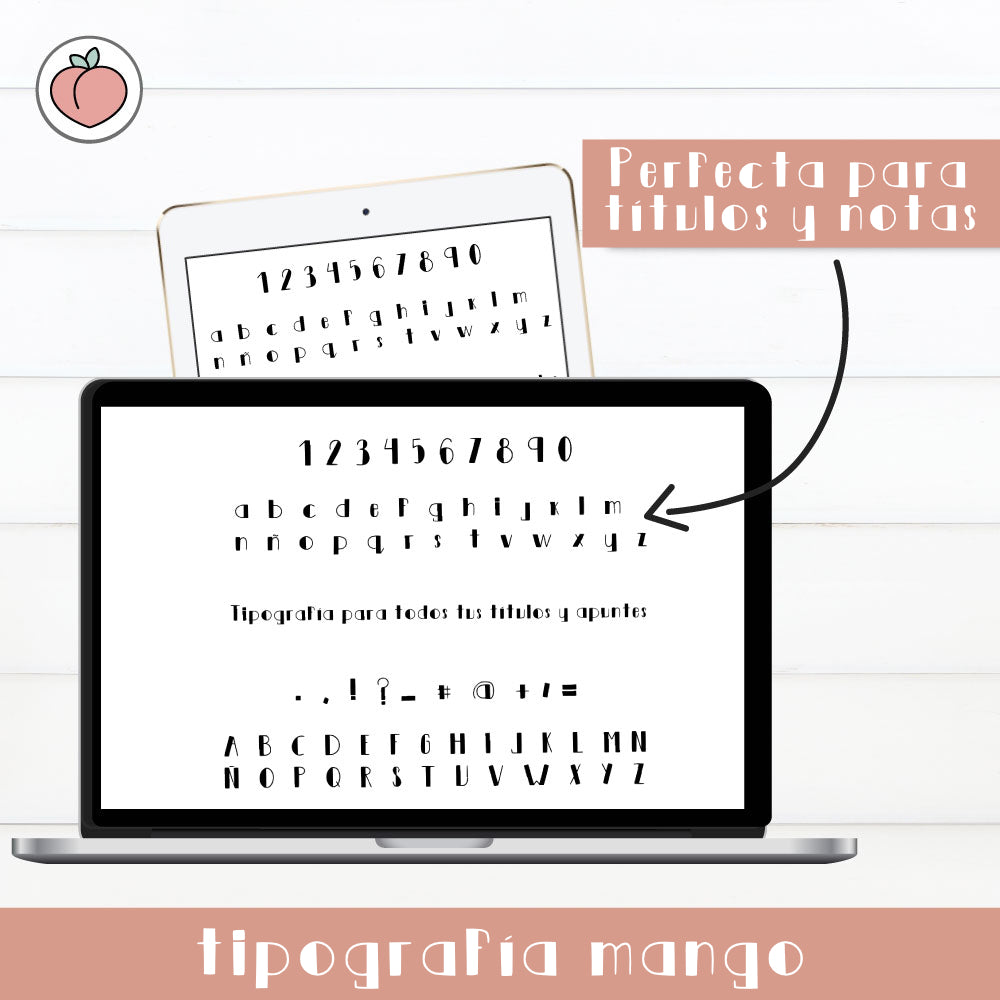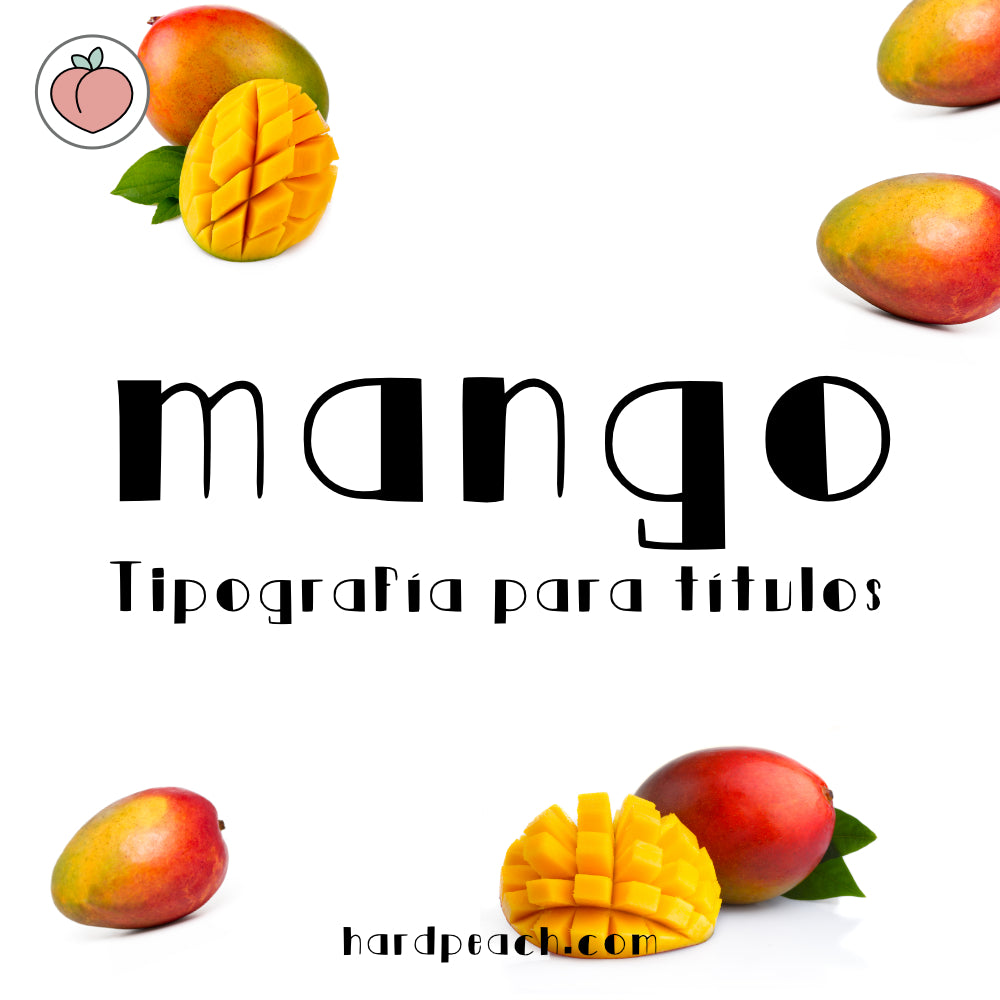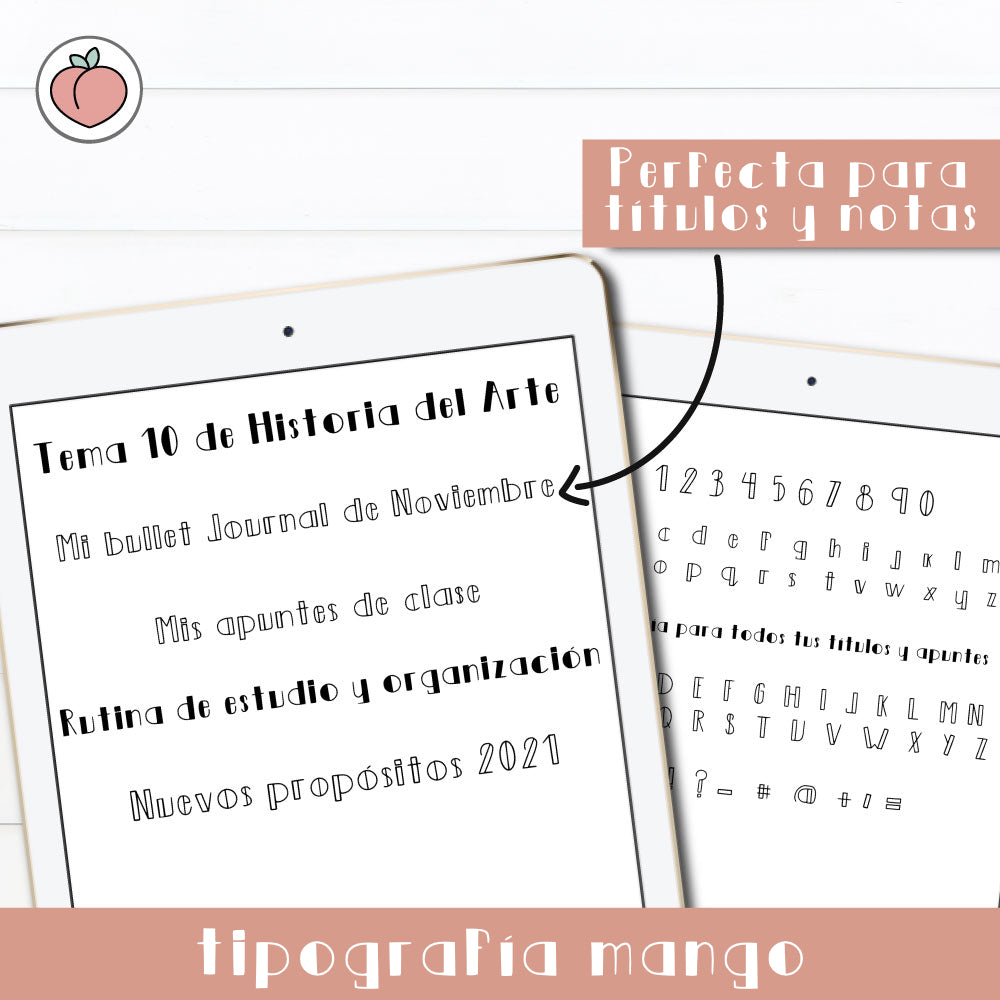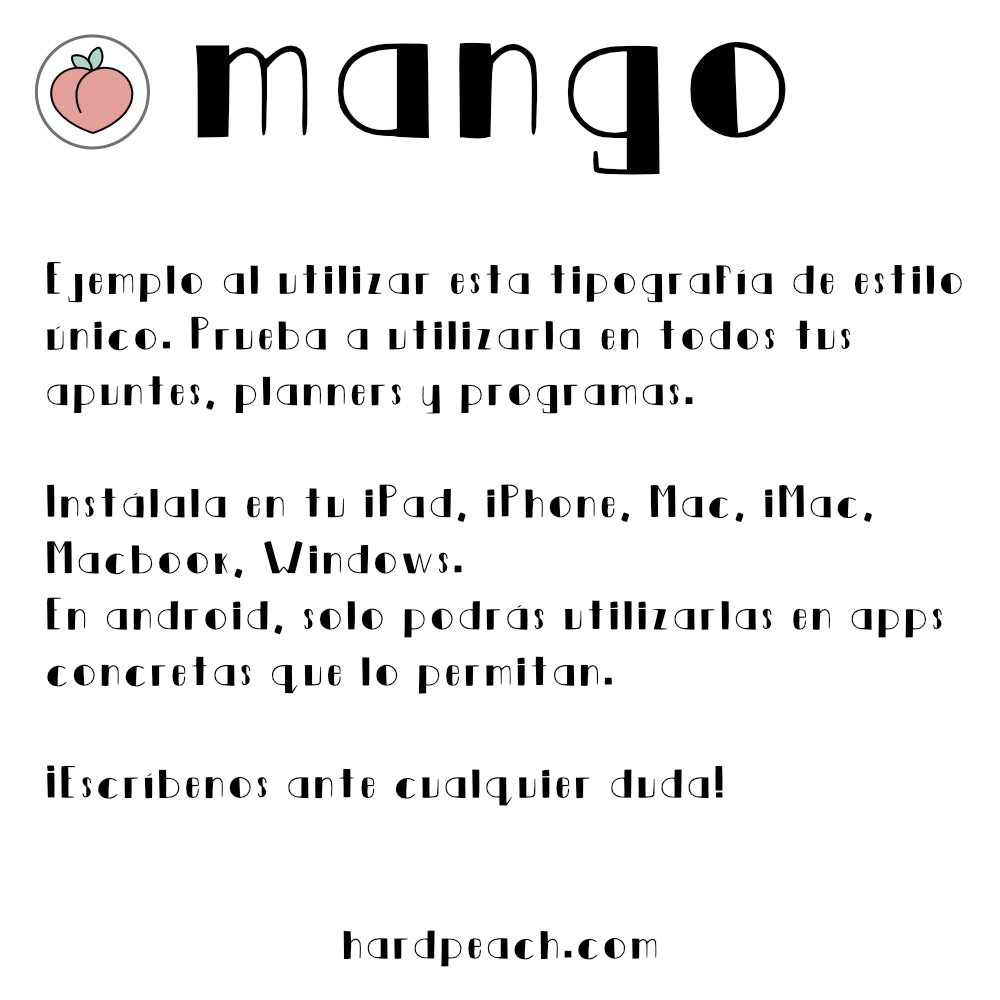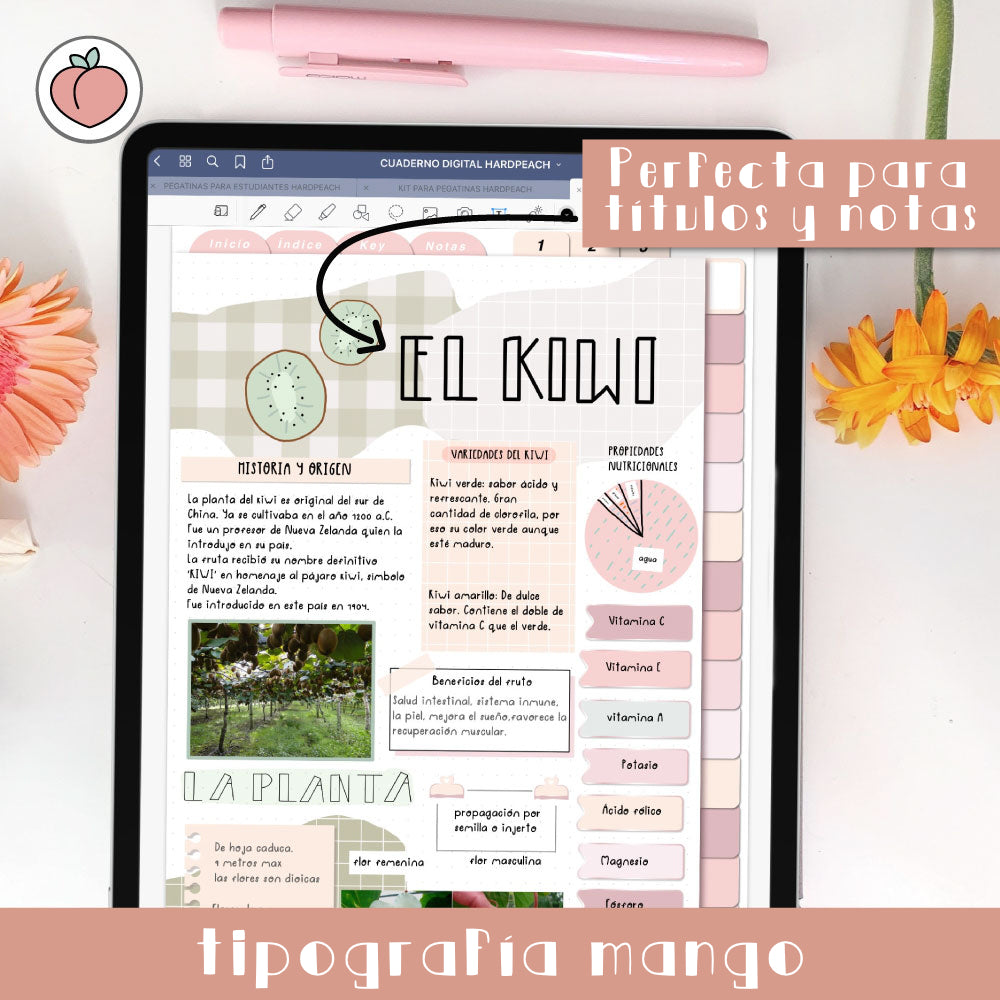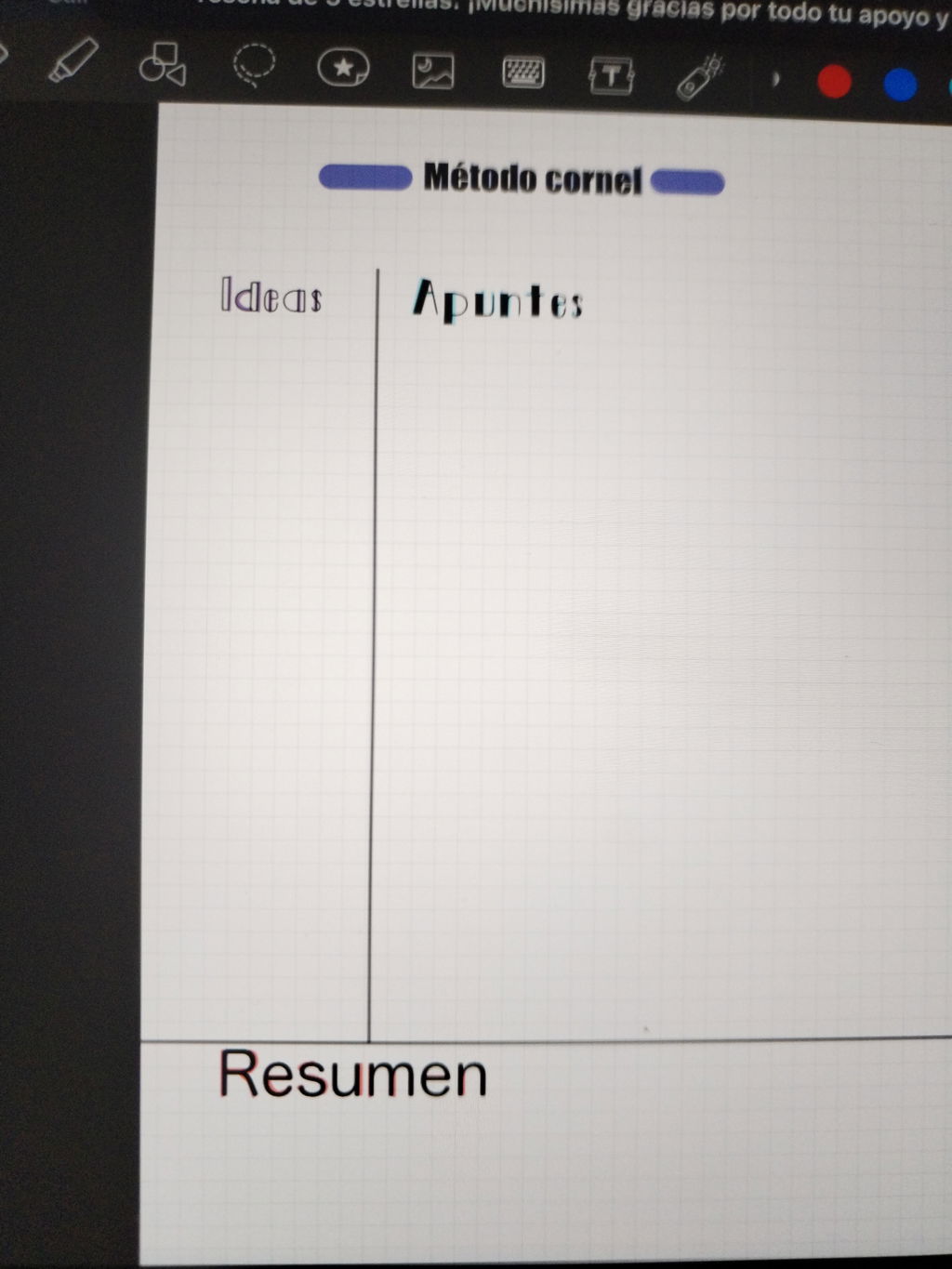
TIPOGRAFÍA MANGO | TRAZOS RECTOS Y MODERNOS PARA TÍTULOS Y ENCABEZADOS
La tipografía Mango es una fuente de trazo recto, limpio y moderno, ideal para darle un estilo profesional y organizado a tus apuntes, títulos, encabezados y secciones de bullet journal. Su diseño sencillo y directo permite que tus textos sean claros, legibles y visualmente atractivos, destacando de manera elegante cualquier contenido.
Incluye el alfabeto español completo, con mayúsculas, minúsculas, números, acentos y símbolos principales, haciendo que sea versátil y útil para todo tipo de escritura académica, profesional o creativa.
Mango es perfecta para estudiantes, organizadores y creativos que quieran que sus apuntes, títulos y secciones de bullet journal tengan un estilo ordenado, moderno y funcional, combinando estética y practicidad en cada página.
Dale a tus proyectos, agendas y bullet journals un toque minimalista y contemporáneo con la tipografía Mango, y convierte cualquier título o encabezado en algo impactante, legible y elegante.
Esta tipografía está en Español incluye todos los caracteres principales, mayúsculas, minúsculas, números, vocales con tildes (español) y algunos signos esenciales. Al estar en Español, no incluye algunas acentuaciones de otros dialectos o idiomas.
Esta tipografía cuenta con los siguientes caracteres:
Abecedario de la A a la Z
Números del 0 al 9
Signos de puntuación más utilizados en Español
Signo de interrogación y exclamación
Versión en negrita